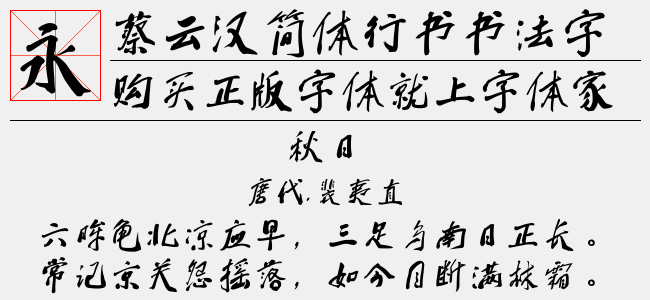
蔡云汉简体行书书法字体
字体名称:蔡云汉简体行书书法字体
书体类型:手写体
蔡云汉简体行书书法字体
蔡云汉简体行书书法字体是一款具有很接地气的手写中文字体,她比较适合用于相关的广告设计,PS软件内嵌以及海报设计应用等,字体家网站是一家专业发布字体下载和免费字体下载和正版授权的字体网站,有叶根友字体以及汉仪字体,方正字体等。